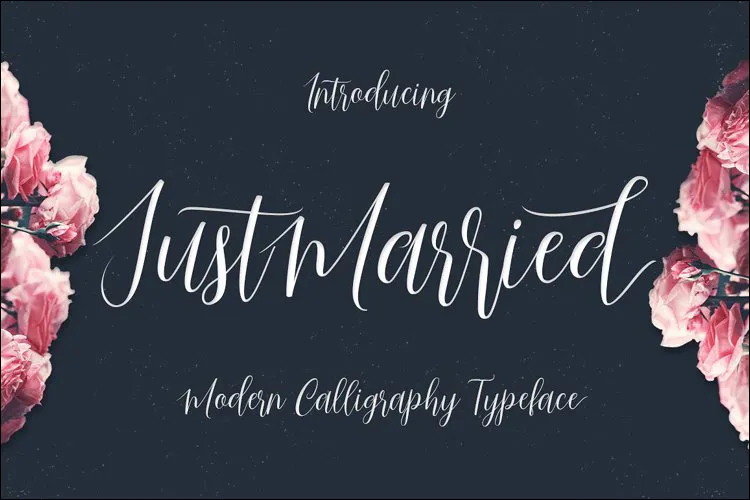
Momen spesial seperti pernikahan, ulang tahun, khitanan, atau lainnya pasti dimulai dengan sebuah undangan. Desain undangan yang menarik dan unik dapat dengan mudah menarik perhatian para penerima undangan. Selain pemilihan warna dan gambar, penggunaan font juga berperan penting dalam menciptakan kesan yang relevan dengan tema undangan.
Font yang keren dan unik dapat meningkatkan kesan elegan, modern, atau bahkan lucu pada undangan, baik digital maupun cetak. Namun, tidak semua font yang keren cocok untuk dijadikan desain kartu undangan. Oleh karena itu, dalam artikel ini, kami telah merangkum secara khusus 33 font undangan keren dan gratis yang cocok untuk berbagai tema undangan. Yuk, kita lihat daftarnya!
Font pertama adalah Sacramento, font semi tegak bersambung yang memiliki kesan formal namun tetap casual, cocok untuk digunakan pada undangan acara semi formal.
Font kedua adalah Sweet Sensations, font yang memiliki kesan bold dan elegan, cocok untuk mempercantik desain kartu undangan pernikahan.
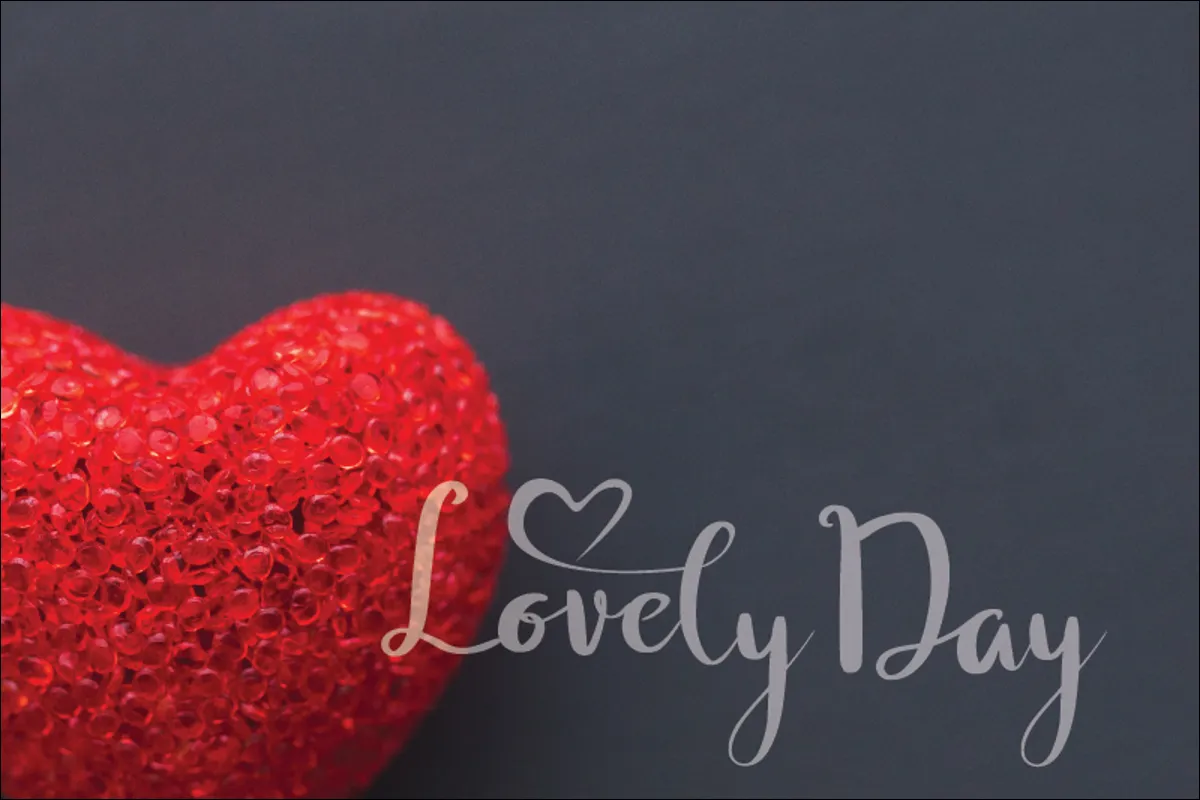
Selanjutnya adalah font Lovely Day, memiliki variasi lengkungan dan bentuk love, cocok untuk digunakan pada font undangan pernikahan.
Jika Anda ingin bentuk font yang sederhana namun tetap lembut dan elegan, jenis font ini akan menjadi pilihan yang cocok untuk desain undangan Anda.
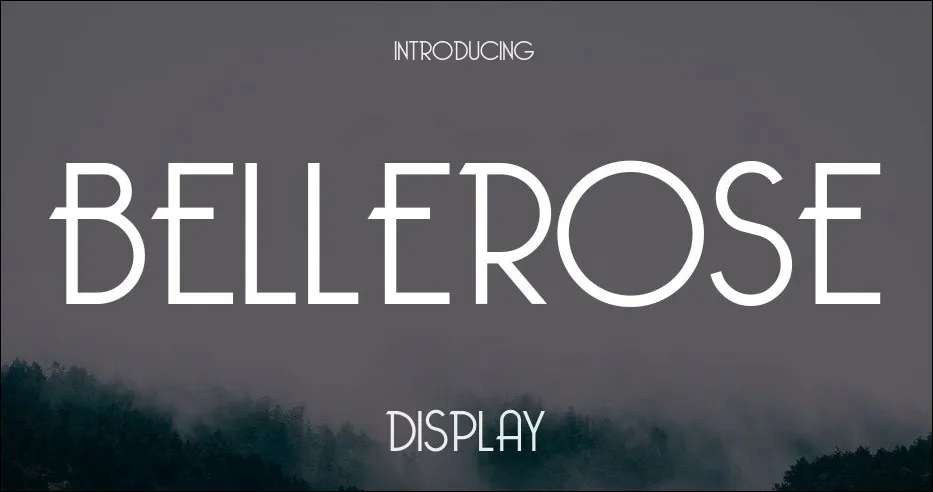
Bellerose adalah font yang memiliki gaya yang elegan dan mewah. Cocok digunakan untuk undangan formal seperti pernikahan atau acara khusus lainnya. Font ini memiliki karakteristik huruf yang anggun dan terbaca dengan jelas.
Caviar Dreams adalah font yang modern dan bersih. Dengan desainnya yang sederhana namun elegan, font ini cocok digunakan untuk berbagai jenis undangan, mulai dari yang formal hingga yang lebih santai.
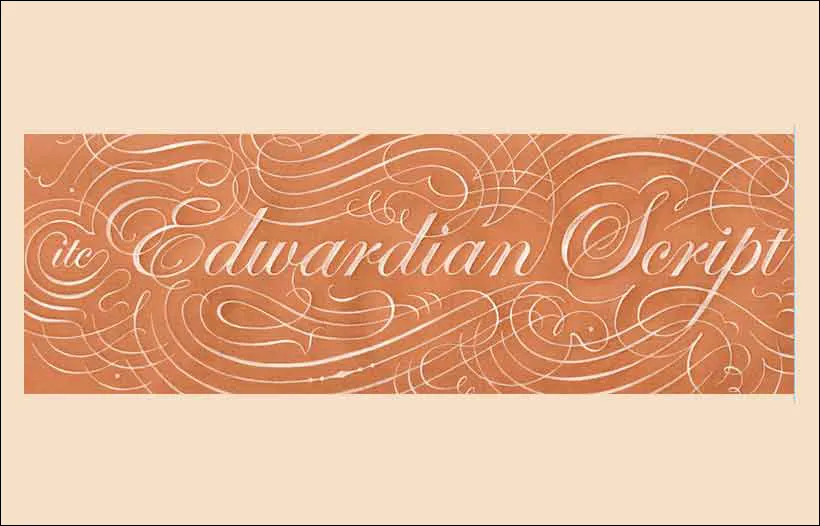
Edwardian Script adalah font yang menghadirkan nuansa klasik dan romantis. Dengan gaya tulisan yang melengkung dan detail yang halus, font ini cocok untuk undangan pernikahan atau acara lain yang membutuhkan sentuhan kemewahan.
Blessed Day adalah font yang memiliki gaya yang manis dan ramah. Cocok digunakan untuk undangan perayaan seperti ulang tahun atau pesta kecil. Font ini memberikan kesan yang hangat dan menyenangkan.
Clarista adalah font yang simpel namun elegan. Dengan desain yang bersih dan mudah dibaca, font ini cocok digunakan untuk undangan-acara formal maupun informal.
Just Married adalah font yang menghadirkan nuansa kebahagiaan dan kehangatan. Dengan desain yang lucu, font ini cocok digunakan untuk undangan pernikahan atau acara lain yang meriah.
Loveline Glamour adalah font yang penuh dengan nuansa romantis dan glamor. Dengan gaya yang mengalir dan detail yang anggun, font ini cocok digunakan untuk undangan pernikahan atau acara khusus lainnya.
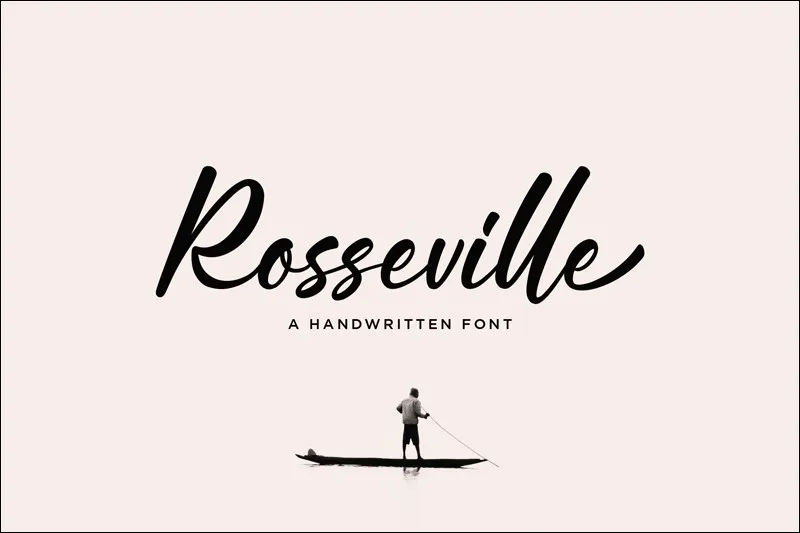
Rosseville adalah font yang memiliki gaya yang vintage dan berkelas. Cocok digunakan untuk undangan-acara yang mengusung tema retro atau klasik. Font ini memberikan sentuhan nostalgia yang unik.
Windsong adalah font yang menghadirkan nuansa alami dan santai. Dengan desain yang mengalir seperti tulisan tangan, font ini cocok digunakan untuk undangan-acara yang berlangsung di luar ruangan atau dengan tema alam.
Candlescript adalah font yang anggun dan romantis. Dengan gaya yang mengalir dan detail yang halus, font ini cocok digunakan untuk undangan pernikahan atau acara khusus lainnya yang membutuhkan sentuhan kelembutan.
Harbell adalah font yang memiliki gaya yang elegan dan mewah. Cocok digunakan untuk undangan formal seperti pernikahan atau acara khusus lainnya. Font ini memberikan kesan yang anggun dan terbaca dengan jelas.
Just Because adalah font yang sederhana namun menarik. Dengan desain yang unik, font ini cocok digunakan untuk undangan-acara informal atau yang bersifat intimate.
Olivia adalah font yang penuh dengan kelembutan dan kesan romantis. Dengan gaya yang mengalir dan detail yang halus, font ini cocok digunakan untuk undangan pernikahan atau acara khusus lainnya.
Madison adalah font yang modern dan stylish. Cocok digunakan untuk undangan-acara yang ingin tampil trendi dan up-to-date. Font ini memberikan kesan yang segar dan berkelas.
Margueritas adalah font yang menghadirkan nuansa yang menyenangkan dan ceria. Dengan desain yang lucu dan berwarna, font ini cocok digunakan untuk undangan-acara yang berlangsung dengan suasana yang hangat.
Anastasia Script adalah font yang memiliki gaya yang anggun dan romantis. Cocok digunakan untuk undangan pernikahan atau acara khusus lainnya yang ingin menampilkan sentuhan kelembutan.
Dalam membuat desain undangan, selain memilih font yang tepat, kita juga harus memperhatikan pemilihan warna dan gambar yang sesuai dengan tema undangan.
Banyak aplikasi yang bisa kita gunakan untuk membuat desain undangan. Namun, umumnya orang-orang menggunakan Canva, Microsoft Word, PowerPoint, Picsart, dan Adobe Photoshop.